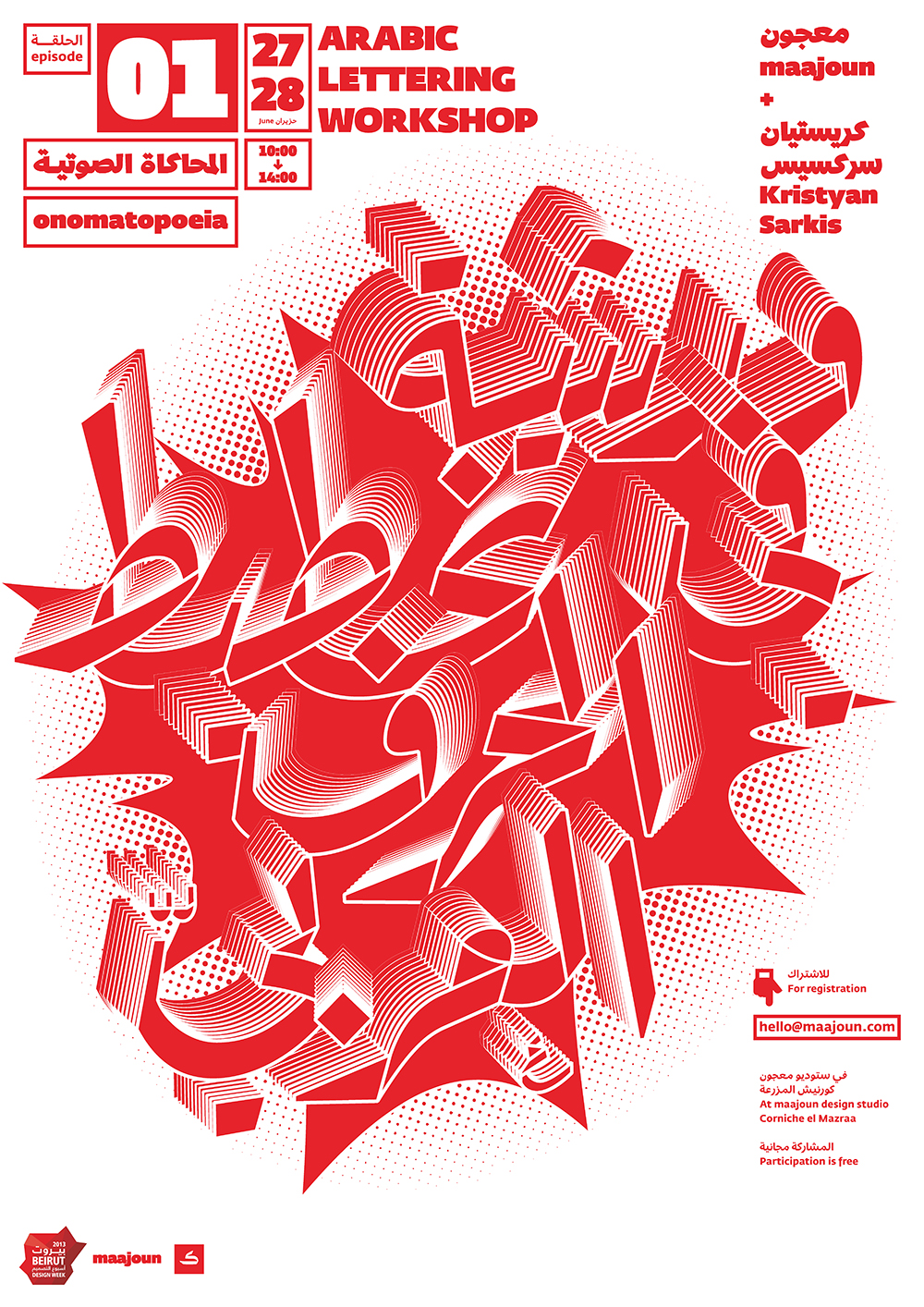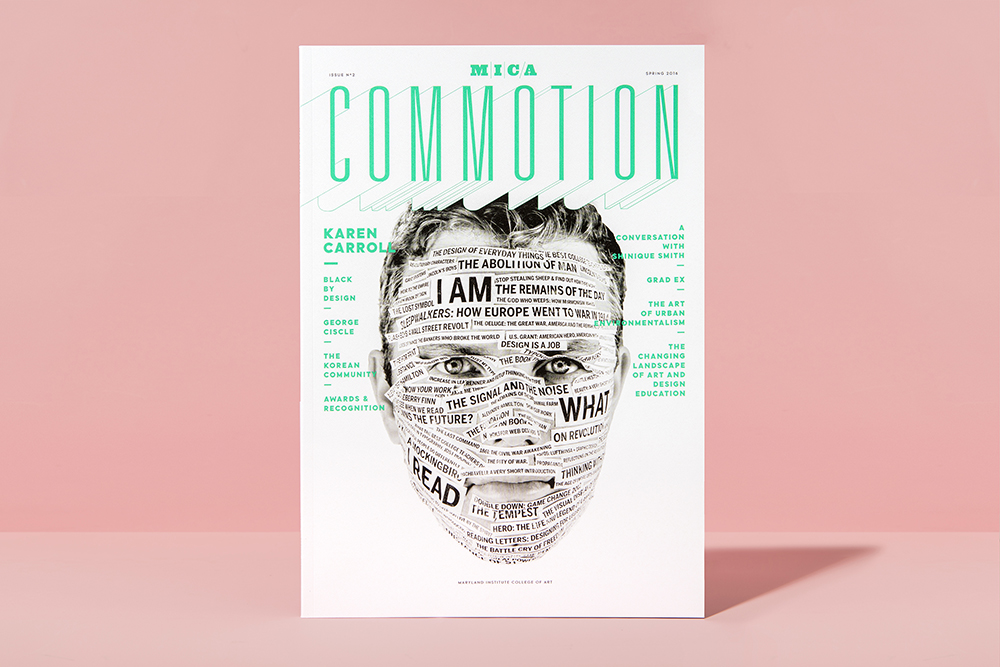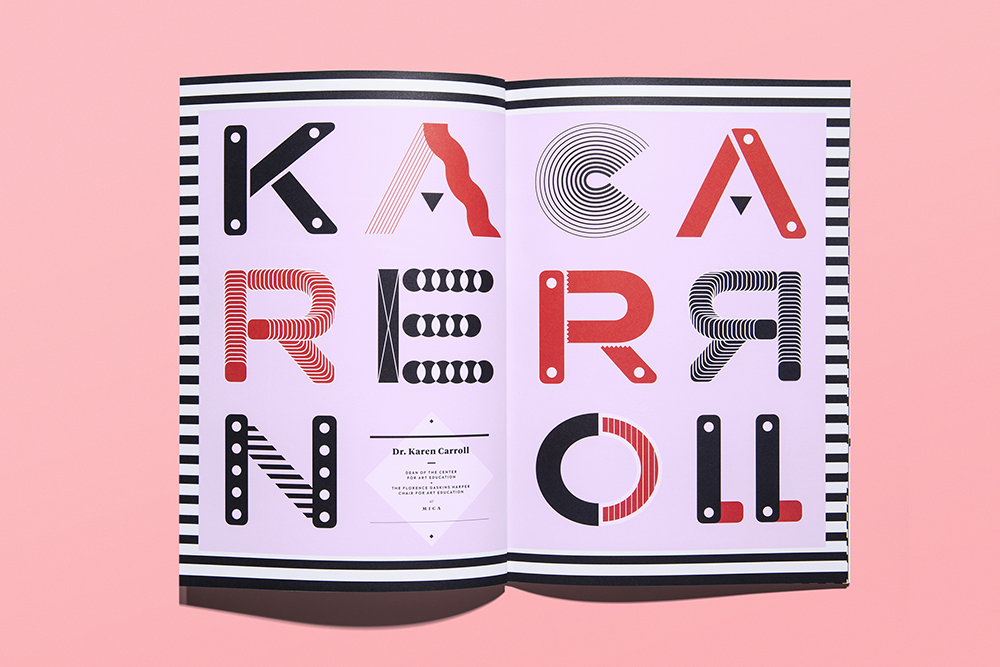
타입 디렉터스 클럽 뉴욕_2017 서울 전시
타입 디렉터스 클럽 뉴욕 Type Directors Club New York(이하 TDC)은 1946년 이래로 매년 우수한 디자인으로 구성된 공모전 수상작들을 전 세계에 전시하며 모든 형태의 타입 디자인 발전에 기여해왔다. TDC 뉴욕의 국내 전시는 2012년부터 삼원페이퍼갤러리에서 진행했으나, 올해는 접근성을 고려해 충무아트센터에서 열렸다.
디자인으로 소통하는 타이포
앞서 말했듯, 서체 디자인은 글자 자체의 의미를 이해하지 못하더라도 ‘디자인으로’ 소통할 수 있는 힘을 가지고 있다. 여기 전시장 입구에서부터 관람객의 눈길을 사로잡는 작품이 있다. 바로 아라빅 레터링 워크숍 Arabic Lettering Workshop 시리즈다. 척 보면 그것이 아랍 서체라는 것을 알 수 있지만, 가만히 들여다보면 어떤 그림처럼 보이기도 한다. 아랍 서체는 한 문화권에서 공용으로 사용하는 ‘문자’라는 틀을 넘어 디자인적으로 새롭게 해석될 수 있는 잠재력을 가진 소재로 평가받고 있으며, 이미 아랍 서체의 강한 표현력에 이끌린 여러 타입 디자이너들이 큰 관심을 보이는 중이다.
ARABIC LETTERING WORKSHOP
Beirut, Lebanon, New York, and Amsterdam
디자인: Khajag Apelian, Yara Khoury, Wael Morcos, and Kristyan Sarkis
그래픽디자인:Lara Balaa
<콴두>는 훌륭한 캘리그래피 대가인 알 콴두시 Al Qzandusi에 대한 오마주로 만들어진 작품이며 동시에 단단하면서도 유동적인 특징을 지닌 마그레브(북아프리카 지역)의 캘리그래피 스타일에 대한 연구라고 한다. 단단하면서도 유동적이라는 말은 얼핏 말이 안 되는 것처럼 보이지만, <콴두>에서 조화를 이루고 있는 아랍 서체와 라틴 서체, 티피나프 서체를 보고 있자면 그 말에 고개를 끄덕이게 된다. 언어를 담은 문자로서의 의미를 각자 단단히 지키고 있으면서도, 미학적으로 또 디자인적인 표현 안에선 하나의 작품을 자연스럽게 이루기 때문이다.
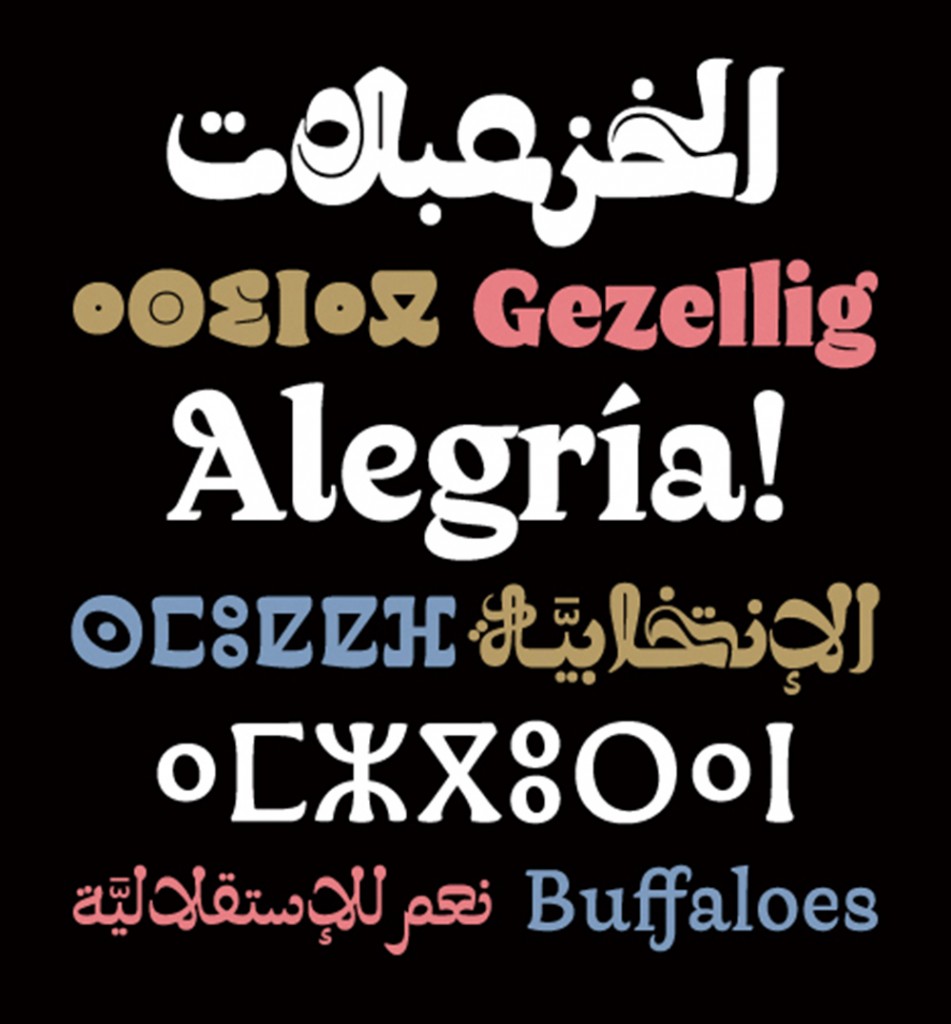
QANDU
Lebanon and Amsterdam
아랍 서체 디자인: Kristyan Sarkis, Lebanon and Amsterdam
라틴 서체 디자인: Laura Meseguer, Barcelona
티피나프 서체 디자인: Juan Luis Blanco—Zumaia, Spain
서체 제작사: TPTQ Arabic TPTQ-Arabic.com—The Netherlands
<링거링 폰트>는 시인인 바이 Bai가 남편을 생각하는 어느 마을의 부인에 대해 쓴 시 ‘소비뇽 블랑(프랑스 보르도 지방의 청포도)’을 모델로 삼았다. 이 폰트의 이름이기도 한 ‘아카시아 링거링’은 실제적으로 붓 획과 붓 형태의 창작, 굽이침, 품음, 획 사이에서 표현되는 부인의 감정의 교차점을 묘사하였다. 또한 여기서 인상 깊은 점 또 하나는 주제에 따라 자칫 감상적으로 흘러가는 것이 아니라, 미니멀리즘 하게 서체의 형태, 주제에게 잠식되지 않은 ‘서체의 몸’을 그대로 보여주는 점도 꼽을 수 있다.
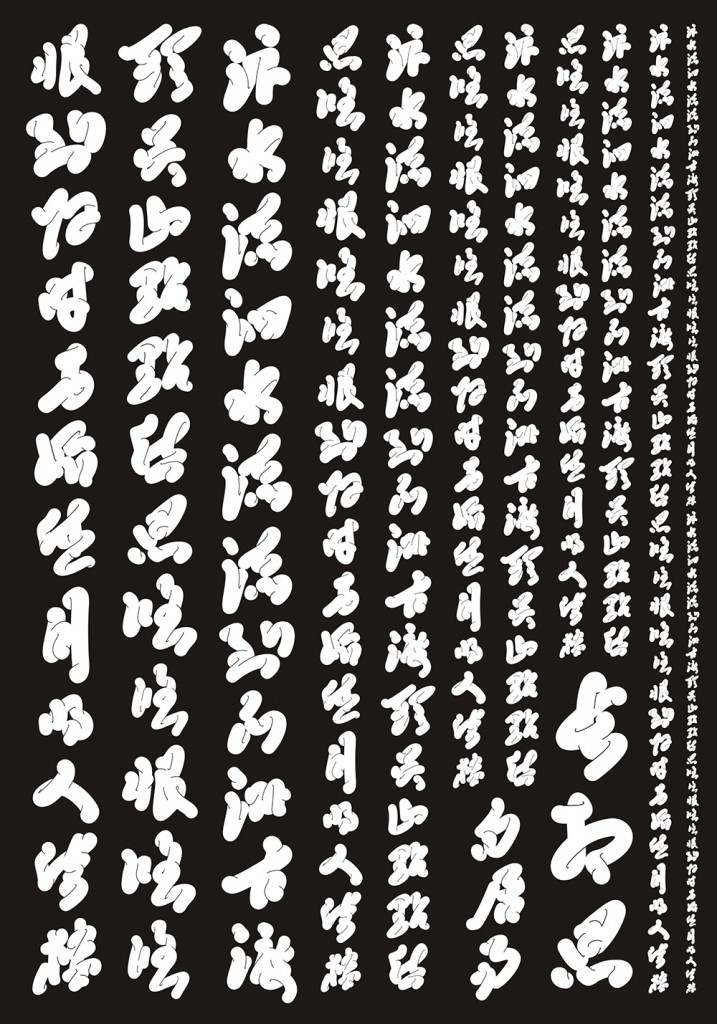
LINGERING FONTS
China
디자인: Zhang Weimin, Shenzhen
클라이언트: WESUN Culture Communication
경쾌한 아이디어, 타이포
책 표지를 독자가 매번 다르게 만들 수 있다면 어떨까? 그것도 직접 손을 사용하여 말이다. 책에 대한 감각적인 접근이 돋보이는 이 책은 대만에 있는 NTUST 건축학교의 ‘연간 디자인 포트폴리오’다. 독자는 새로운 아이디어와 콘셉트를 나타내기 위해 ‘고무줄 알파벳’으로 디자인할 수 있다.
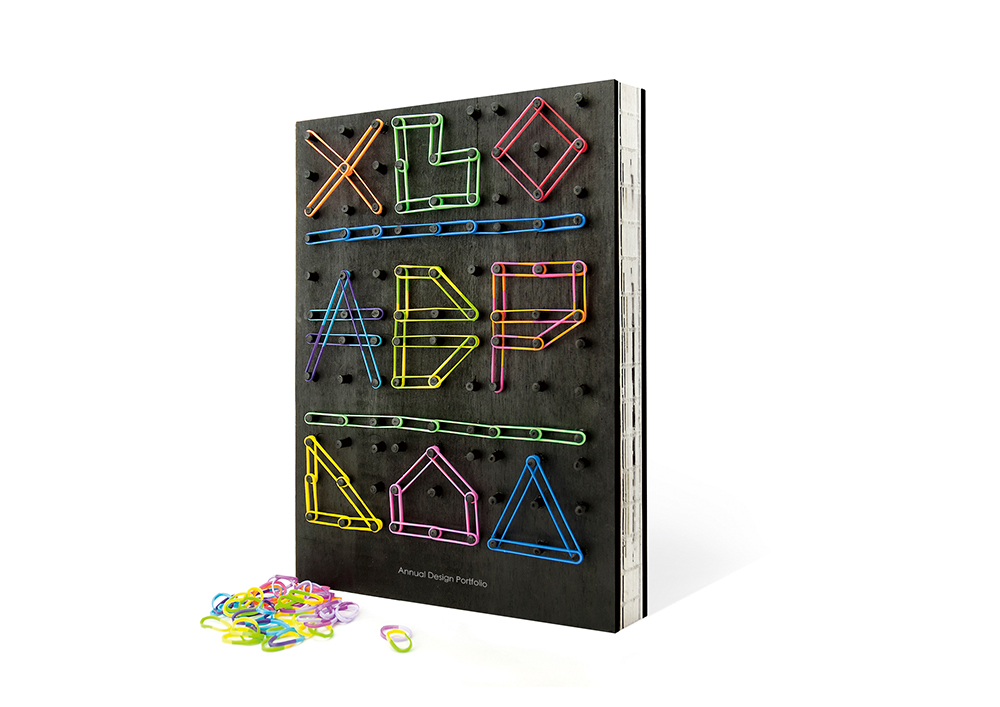
Original
Taiwan
디자인: Yan-Ting Chen
디자인 회사: Yantingchen Design
클라이언트: NTUST Architecture
클라이언트인 위트랜스퍼 WeTransfer는 파일 전송 시스템을 ‘만질 수 있는 유형’으로 만들어서 창의적인 가치를 높이길 원했다. 디자인을 맡은 스튜디오 프리스 Studio Frith는 기본적인 브랜딩 북과는 달리, 디자인의 미학을 좀 더 ‘재미있게’ 드러낼 수 있길 원했다. 따라서 그들은 책에 맞는 맞춤형 타이포그래피를 발전시켰고, 볼드체와 밝은 색상을 사용하였다. 또한 같은 시스템으로 엽서와 가방에도 적용하였다. ‘Doubt, Time, Magic’이 적힌 이 서체들은 누군가에게 전송이 되는 것처럼 길게 늘어져 있다.
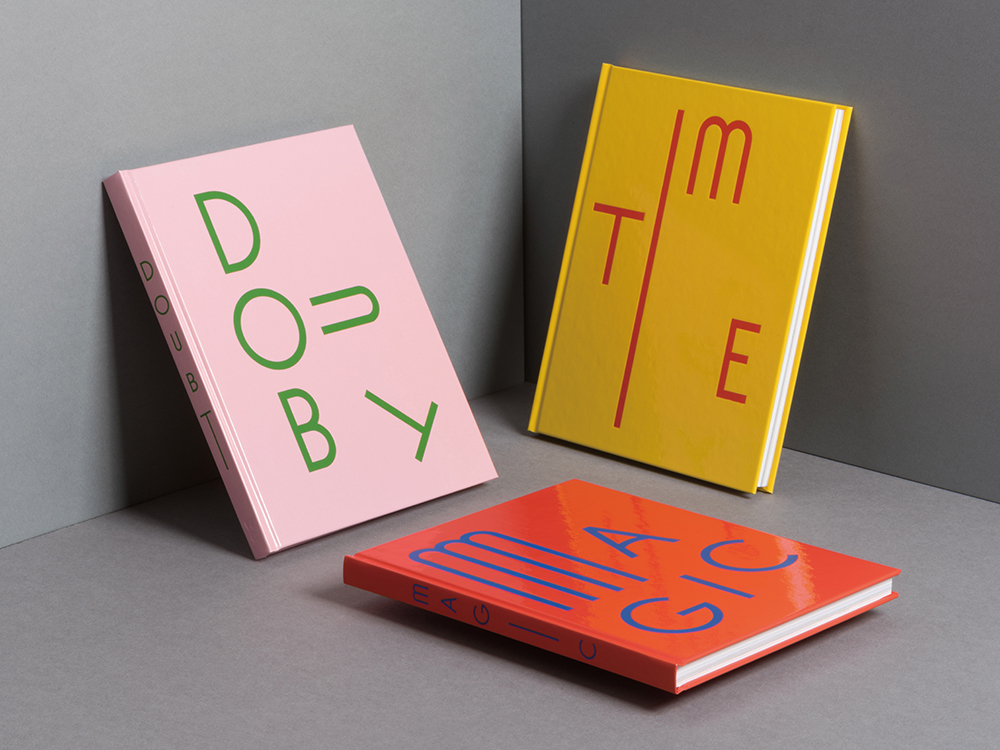
Long Face
London
디자인: Studio Frith
클라이언트: WeTransfer
<소란>에서의 서체는 그저 잡지를 구성하는 부속품이 아니라 잡지의 주체이며 콘텐츠이다. 밝은 색깔과 충돌적인 레이아웃, 두껍고 힘 있는 글씨체 그리고 일러스트레이션을 시각적으로 채택하면서, <소란>은 독자들로 하여금 창의적인 여행을 떠나게 한다. 독자들은 바로 이러한 지점에서 영감을 얻는데, 이런 광범위한 영감을 얻는 것은 역동적이고 보람될 뿐 아니라 무질서하며 혼란스러울 수 있다. <소란>은 디자이너에게 영감을 주고, 또 그것으로부터 영감을 얻은 디자이너로부터 탄생되는 잡지라고도 할 수 있다.
Tiempo Tiempo Headline, Tomica, Tiempos, and custom
Washington, D.C.
아트디렉션: Mariela Hsu
선임디자이너: Lillian Ling
크리에이티브 디렉터: Pum Lefebure
대표: Jake Lefebure
디자인 대행사: Design Army
클라이언트: Maryland Institute College of Art (MICA)